使用字体:理杏圆黑简系列
使用位置:包装各处
上海妮飘以高品质和唯美艺术的包装设计而广受消费者喜爱,在中国市场也屈指可数的家庭用纸制造商。理杏圆黑简系列字体被用于其新卷筒卫生纸「印象主义」的产品包装上,成为设计中的亮点!
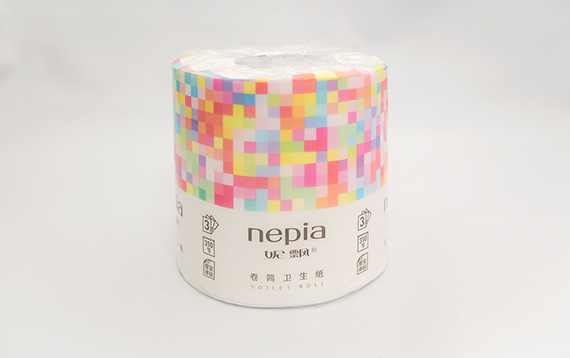
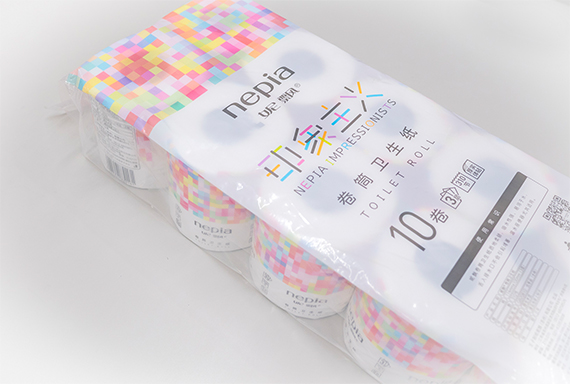
理杏圆黑简系列共7种粗细。无论是作为品牌文字修饰或是重点形式,都能使整体设计显示出亲切可爱,优美悦目的感受。简洁大方的字体,与设计相辅相成,让本就出色的设计,更添魅力,进一步提升产品和品牌的精致唯美的品质感。